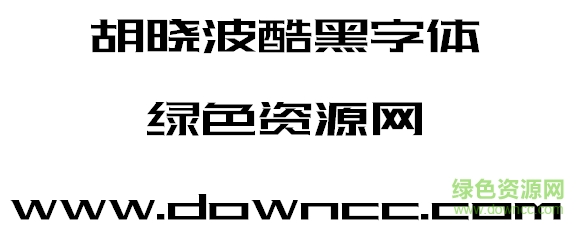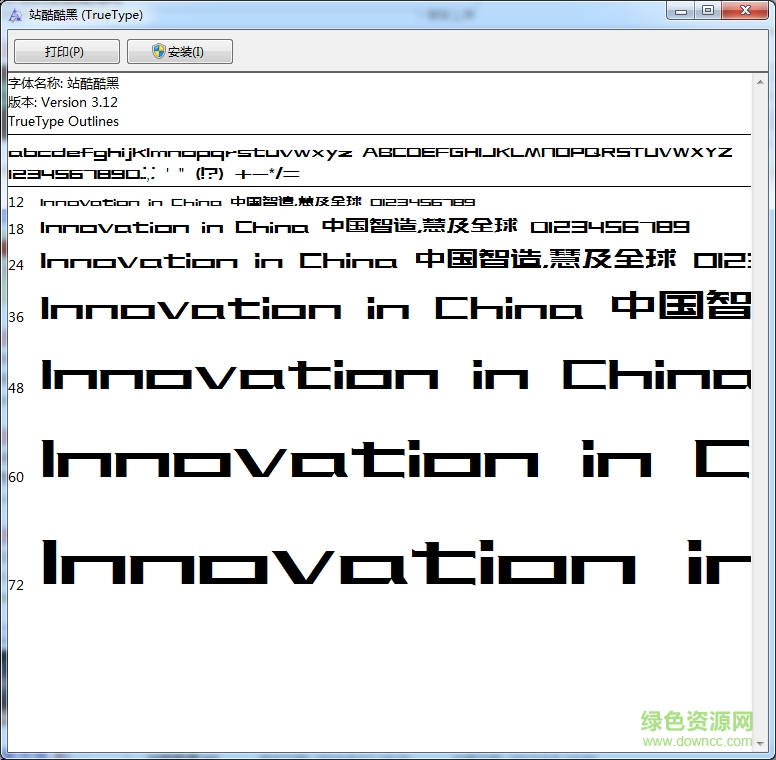
胡曉波酷黑是胡曉波攜手站酷設(shè)計(jì)師們共同打造的藝術(shù)字體,大氣磅礴的字形讓您的廣告設(shè)計(jì)、書面印刷、文字打印更顯深厚魅力,綠色資源網(wǎng)免費(fèi)提供下載服務(wù)!
胡曉波酷黑即站酷酷黑體驗(yàn)版,字形筆畫粗獷有力、用寬扁型的字面構(gòu)建出厚重的字體形態(tài),筆畫細(xì)節(jié)上的修飾既增強(qiáng)了字體的設(shè)計(jì)感,又讓字體多了一些小小的精致感。這套字體的中宮非常飽滿,使得文字之間的排版組合非常醒目好看。
恰逢在站酷十周年之際,橫空出世。該字體由胡曉波發(fā)起,字游工作室成員進(jìn)行基礎(chǔ)字形設(shè)計(jì),胡曉波設(shè)計(jì)班十名學(xué)員共同設(shè)計(jì)完成。